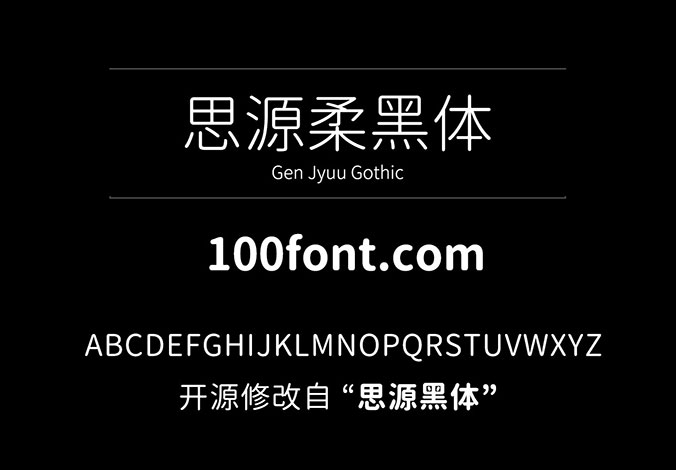
思源柔黑体(源柔ゴシック)和思源真黑体(源真ゴシック)是日本 自家製フォント工房基于开源字体“思源黑体”修改制作衍生而来,支持简体中文、繁体中文以及日文三种语言。两款字体都是开源免费的,应用场景非常广泛。
思源柔黑体一共发布了 3 个版本,分辨是标准版、L、X。它们的区别在于圆角的圆润程度不同,L 圆角最小 (最尖),X 圆角最大 (最圆),而标准版则是介于两者之间。每个版本都有 7 种字重,3种字形样式 (包括等宽字体)。